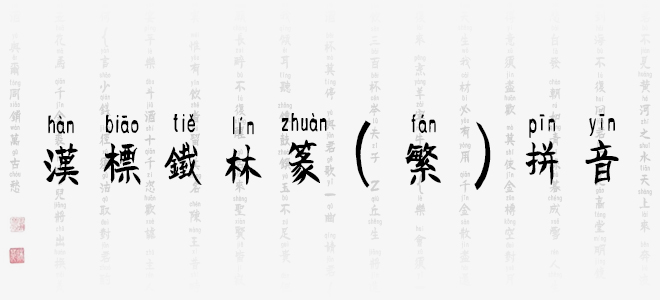
漢標(biāo)鐵林篆(繁)拼音是一款在漢標(biāo)鐵林篆繁的基礎(chǔ)上添加了拼音標(biāo)注效果的藝術(shù)字體,該字體巧緣于三國(guó)書(shū)法家衛(wèi)瓘,衛(wèi)瓘乃王羲之恩師衛(wèi)夫人之伯父,他善隸書(shū)、章草,始創(chuàng)柳葉篆,被稱為北派始祖。今鐵林篆來(lái)源生活,師法自然,終得字體,是衛(wèi)瓘柳葉篆的傳承,更是對(duì)中華文化的弘揚(yáng)與發(fā)展。 作者:段鐵林,德藝雙馨書(shū)法家,中國(guó)書(shū)法家協(xié)會(huì)書(shū)法考級(jí)注冊(cè)教師,中國(guó)書(shū)法學(xué)會(huì)副主席,中國(guó)書(shū)法美術(shù)研究院副院長(zhǎng)等。
漢標(biāo)鐵林篆(繁)拼音體